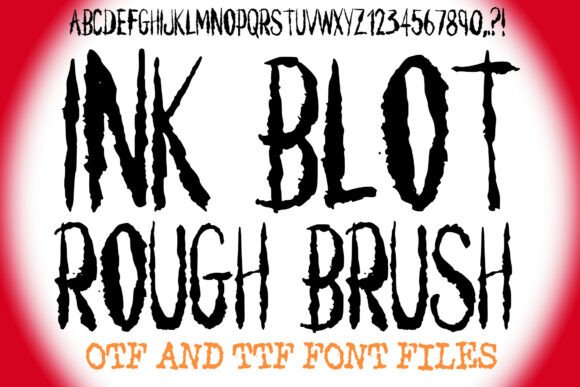
Ink Blot Rough Brush
Doğru tasarım öğelerini bulmak zor olabilir, ancak Ink Blot Rough Brush, çalışmanızı anında bir üst seviyeye taşıyan olağanüstü bir koleksiyon sunar.
İster İsteğe Bağlı Baskı (POD) ürünleri, ister düğün davetiyeleri veya sosyal medya grafikleri oluşturuyor olun, Ink Blot Rough Brush ideal bir uyumdur.